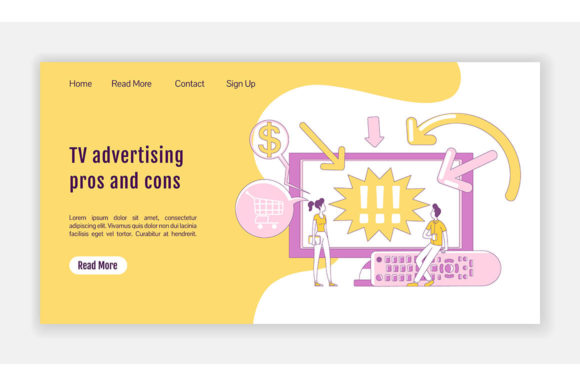
TV Advertising Pros and Cons Page
Việc tìm kiếm các thành phần thiết kế phù hợp có thể là một thách thức, nhưng TV Advertising Pros and Cons Page cung cấp một bộ sưu tập đặc biệt giúp nâng tầm công việc của bạn ngay lập tức.
Được chế tác với độ chính xác cao, TV Advertising Pros and Cons Page cung cấp các vector sạch, kiểu chữ mượt mà và giấy phép thương mại để bạn yên tâm.
Cho dù bạn đang tạo sản phẩm POD (In theo yêu cầu), thiệp mời đám cưới hay đồ họa mạng xã hội, TV Advertising Pros and Cons Page đều là một sự lựa chọn lý tưởng.